Какие шрифты лучше использовать в дизайне визиток?
Меня часто спрашивают, какие шрифты лучше всего использовать в дизайне визиток.
Что-то уже было в статье «7 способов испортить визитку», но есть и еще кое-что.
А не спеть ли мне… эдаким необычным шрифтом, не как у всех?
Визитка делается не с целью удивить людей необычным шрифтом.
Для текста, который должен быть воспринят за доли секунды (имя, фамилия, профессия, контакты) нужно использовать только хорошо читаемые шрифты. Если это смотрится красиво — еще лучше.
В первых двух вариантах использованы шрифты, с которыми знакомы все, — Arial и Times New Roman. Читать их удобно и легко.
В третьем макете «необычные» шрифты сильно затрудняют прочтение текста. Да и выбор их случаен, то есть ничем не обоснован. Какая у этого цель? Видимо, кому-то (директору?) просто так захотелось. Но, вероятно, он не слышал, что дизайн всегда служит решению определенной задачи, а хороший дизайн — незаметен. Тут шрифт никакой задачи не решает, а значит, так делать не надо.
В четвертом макете — симпатичный и ставший модным несколько лет назад шрифт Lobster. На самом деле лучше всего он подходит для меню и рекламы кафе или суши-бара, что доказывает его частое использование именно в таком контексте.
Также он хорош для заголовка, названия или рекламного слогана, но всё меняется, когда его много.
Не набирайте таким шрифтом большое количество текста!
На визитке он может использоваться тоже. Вряд ли это будет карточка адвоката, банкира или чиновника. Если неформальный тон, который задает такой шрифт, — это именно то, что вы хотите передать, используйте его, но помните, что лучше ограничиться одной строкой — например, ФИО:
Получается, «обычные» шрифты лучше?
Это зависит от задачи, но очень часто — да. Если вы делаете строгую визитку, не бойтесь старого Ариала и доброго Таймса, даже если вам кажется, что они выглядят слишком банально и просто, так как они «есть в ворде». Они там есть потому, что это хорошие шрифты. С ними проще сделать красиво и сложнее испортить. Опасаться нужно как раз необычных, непривычных, вычурных, рукописных и декоративных шрифтов. Особенно в визитках и особенно в больших количествах.
Но ведь есть много красивых шрифтов? Как так, совсем нельзя?
Можно. Но только если это не строгая визитка и если надпись, набранная необычным шрифтом:
— подчеркивает стилистику и тематику;
— поддерживает или усиливает сообщение;
— является (или почти является) логотипом;
— помогает решить задачу.
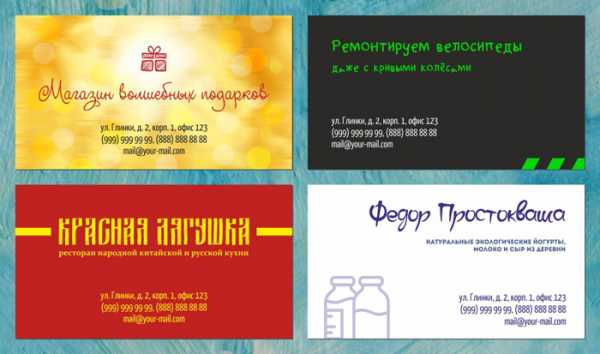
Если вы хотите взять «необычный» шрифт для своей визитки, но не уверены, выполняет ли он хотя бы одно из условий выше (и нужно ли ему их выполнять), забудьте о нем и посмотрите или вспомните, какие шрифты обычно используются для набора книг.
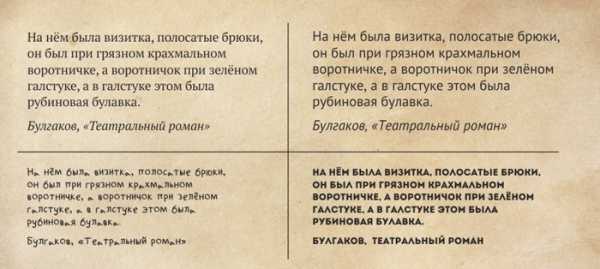
Такие, которые легко читать, как в двух верхних примерах.
Вот самый простой способ разделить шрифты на несколько групп в виде небольшой блок-схемы (не зря же я получал высшее образование по математической лингвистике). Начнем с вопроса «Подходит ли шрифт для набора большого количества текста?»
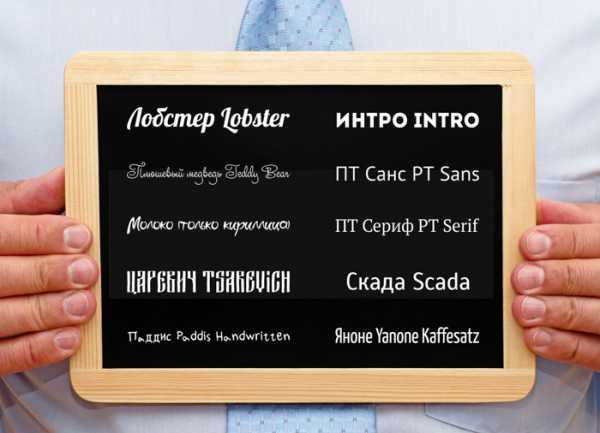
Небольшой гид по использованию шрифтов в визитках
Выбор шрифта – важный момент в создании любого дизайна, так как каждый шрифт вызывает определенные ассоциации. Данный пост является небольшим гидом по шрифтам, предложенным в нашем онлайн конструкторе визиток и использует исторические и другие факты, чтобы показать какие ассоциации эти шрифты вызывают.
C засечками или без
Исторически все шрифты делятся на два больших класса: шрифты с засечками (serif), небольшими черточками на концах букв, и без засечек (sans serif, от французского «без засечек»).
Шрифты с засечками появились в печатном деле гораздо раньше. Засечки были заимствованы из древнеримского написания, где, вероятно, они были побочным эффектом высечки букв на камне. Из-за этого вместо термина serif иногда используют термин Roman (римский) в названии шрифта (например, Times New Roman)
Шрифты без засечек (san serif) еще часто называют Готическими (Gothic), так как готические шрифты имитируют письмо пером, в котором нет засечек, или Гротесками (Grotesque), так как в 19-м веке шрифты без засечек стали часто использовать в заголовках.
Принято считать, что шрифты с засечками более удобны для чтения в больших текстах, в то время как шрифты без засечек более привлекательны с эстетической точки зрения. Поэтому при создании визиток чаще используются шрифты без засечек. Однако все зависит от общего стиля визитки. Например, шрифты с засечками будут хорошо смотреться в винтажных дизайнах.
Шрифты – аналоги
Очень часто встречаются практически аналогичные шрифты (например Arial и Pragmatica). Причина проста – это версии одного и того же успешного шрифта, созданные конкурирующими компаниями – производителями печатного оборудования. Часто название компании-производителя добавляется к названию шрифта (Monotype Cursiva – компания Monotype, Palatyno Lynotype – компания Linotype)
Основные шрифты с засечками
Times New Roman – шрифт с засечками, созданный в 1931 году специально для газеты Times. Times использовала его в течение 40 лет. С тех пор шрифт стал невероятно популярен в газетном деле и книгопечатанье. Если Вы книгоиздатель или хотите, чтобы Ваша визитка ассоциировалась с английской газетой начала XX века или просто хотите придать визитке винтажный стиль, то Times New Roman – ваш выбор. В онлайн конструкторе визиток ЛемонПринт мы предлагаем большое количество вариаций шрифта Times New Roman различной степени «жирности» и ширины.
Courier (аналог: Courier New) – шрифт с засечками, созданный в 1955 году и имитирующий текст, получающийся на механической печатной машинке. Данный шрифт использовался Министерством Иностранных Дел США, а также стал стандартом для телесценариев и для отображения кода компьютерных программ и сообщений на компьютерных терминалах командной строки (то, с чем мы ассоциируем хакеров, набирающих код на черном экране). Как результат, шрифт ассоциируется со способностью выйти за рамки и свободой. Кроме того, отлично подходит для коротких цитат.
Основные шрифты без засечек (Гротески)
Franklin Gothic – шрифт без засечек. Шрифты без засечек появились в 19-м веке под названием Гротески. Отказ от засечек был очень важной вехой в типографике, так как ранее на протяжении многих веков шрифты были с засечками, имитируя рукописный текст пером. Гротески использовались в основном в заголовках, и потому чаще встречаются в жирных вариантах. Franklin Gothic появился около 1902 года и активно использовался в заголовках для книг и газет. Его основное начертание – экстра жирное. Именно оно и представлено в нашем редакторе.
Arial (аналоги: Helvetica, Pragmatica) – это нео-гротеск (современная версия гротесков), шрифтов без засечек. Шрифт Helvetica был создан швейцарским дизайнером Максом Мидингером в 50-60-х годах XX-го века. Этот шрифт вобрал в себя результат таких движений в дизайне как Супрематизм и Конструктивизм, целью которых было упрощение и чистота геометрических форм. Он более округлый и гораздо более пропорциональный, чем классические «старые» Гротески. Шрифт Helvetica получил очень широкое распространение. Arial и Prgamatica – это версии шрифта Helvetica, созданные позднее другими дизайнерскими агентствами. Все три шрифта практически идентичны и идеальны для визиток. В онлайн конструкторе ЛемонПринт мы предлагаем большое количество вариаций шрифта Arial различной степени «жирности» и ширины. Если вы стремитесь к современному и минималистичному дизайну – это Ваш выбор.
Futura (аналог: Futura ParaType), Century Gothic – шрифты из семейства геометрических гротесков. Как видно из названия, эти шрифты основаны на максимально геометрически правильных и простых формах. Появление таких шрифтов, в основном, связано с течением Баухаус. Геометрические гротески наиболее хорошо смотрятся в сочетании с такими же простыми формами. Очень стильные шрифты, но будут хорошо смотреться только на тех визитках, где очень мало текста и много пустого пространства.
Помимо этих основных шрифтов, в нашем конструкторе визиток представлен еще большой набор Гротескных шрифтов различного начертания. Современные (такие, как Play), стилизованные под кисть (такие, как Pollock), имитирующие трафарет (такие, как Glasten) и много других.
Каллиграфические шрифты
Каллиграфические шрифты имитируют рукописный текст. В цифровую эпоху их появилось огромное количество. В нашем редакторе представлены порядка 10 различных вариаций каллиграфических шрифтов, имитирующих современное, старинное и даже детское рукописное письмо, включая всем известный Lobster. Такие шрифты смотрятся очень красиво, однако подойдут больше людям творческих профессий. Кроме того, текст, написанный каллиграфическими шрифтами, очень сложно читать. Поэтому при создании визитки используйте их для одного или двух самых крупных слов (например, имени и фамилии) и постарайтесь использовать максимальный возможный размер шрифта.
Интересно, что до компьютерной эры большинство логотипов, магазинных и других вывесок были сделаны не печатным текстом (из-за технической сложности), а выгравированы мастерами или художниками и подражали рукописным текстам различных эпох, что выглядело очень элегантно. Например, посмотрите на надписи на логотипе Cadillac или даже Ford. Cо второй половины 20-го века ситуация изменилась, и на логотипах стал чаще встречаться печатный текст. Но, возможно, Ваше лого или название компании, должно быть написано именно каллиграфическим шрифтом?
Читайте также
В каком формате лучше посылать макеты в типографию для изготовления печатной продукции?www.lemonprint.ru
Шрифты для визиток / Блог — визитки, печать визиток, заказать визитки
Как правильно выбрать шрифт для визитки
Как выбрать шрифт для визитки? Какой размер шрифта считается самым оптимальным? Можно ли использовать разные шрифты на визитной карточке? И вообще, как с помощью шрифта сделать визитку по-настоящему привлекательной? На эти и другие вопросы вы найдете ответы в этой статье.
На данный момент существует огромное количество самых разнообразных шрифтов, а их библиотека постоянно пополняется, предоставляя дизайнерам все больше пространства для творчества и интересных решений. Однако, не стоит забывать о том, что простота — ключ к элегантности! Поэтому, давайте сразу поговорим о том, какие шрифты не стоит использовать в своем дизайне. Плохой шрифт – плохой имидж.
- Comic Sans – слишком детский шрифт. Разве что, вы рекламируете товары или услуги для детей;
- Papyrus – комментарии излишни, не предназначен для деловых документов. Или в качестве материала для печати вы намерены использовать древнеегипетский папирус?)
- Arial – потому, что он везде! Вместо него используйте Calibri;
- Courier New – предназначен для написания сценариев. Если вы не хотите, чтобы текст на вашей визитке напоминал титры к голливудскому блокбастеру, не стоит использовать этот шрифт.
Так, какой же шрифт выбрать? Мы предлагаем простое решение – воспользуйтесь конструктором vizitka.ua! Сотни эксклюзивных шаблонов уже готовых использованию! С помощью нашего конструктора вы сможете с легкостью отформатировать свою визитную карточку, применив к ней самые разнообразные шрифты. Попробуйте, вам понравится! Итак, если:
— ваш бизнес связан со сферой науки, образования, юриспруденцией используйте Verdana;
— для всех специальностей, связанных с природой лучший выбором, станет Georgia;
— для сферы красоты и здоровья подойдет любой красивый прописной шрифт, например, Veles.
Используйте шрифты с умом, сделайте ваш дизайн простым, понятным и уникальным! Успехов Вам!
www.vizitka.ua
Поиграем шрифтами: как выбрать хорошую гарнитуру для визитки
Маленькая визитка — товар, который заказывают часто и сразу помногу. В большинстве случаев заказчик приходит в типографию с готовым макетом визитной карточки, с которого мы и печатаем. Но честное слово, глядя на некоторые макеты, особенно на их шрифтовую часть, становится откровенно жалко тех, кому эти визитки будут вручаться.
Мы уже писали здесь про пять правил корпоративной визитки. Давайте сегодня подробнее поговорим о выборе шрифта для этого важного бизнес-аксессуара.
Наш дизайнер, милая и нежная, но чересчур эмоциональная Маша Гутенберг уже высказала в своем ЖЖ мнение на тему «поиграть шрифтами» и свои соображения об использовании в дизайне полиграфии оригинальных шрифтов (осторожно: 18+ и местами очень непечатно). Мы постараемся рассказать о том же самом, но более литературно.
Главное правило — легко прочитать
Зачем вообще нужна визитка? Точно и легко передать кому-то контактную информацию. Поэтому при подборе шрифта для визитки надо помнить два правила:
- Текст должен легко читаться. Вы должны четко различать все символы, буквы и цифры.
- Текст должен быть достаточно крупным. Мелкий бисер никто не будет разглядывать в лупу.
На визитной карточке размером 90×50 мм, не так много места, на котором надо разместить контактные данные, имя и фамилию, а также оставить место для корпоративной идентификации или элементов оформления. Всё это должно смотреться органично и не мешать друг другу.
Для визиток рекомендуется использовать шрифт 10-14 кегля. Это оптимальный размер черного шрифта на белом фоне, который человек с достаточно хорошим зрением прочтет без труда. Мы не рассматриваем цветовые решения и контрастность текста и фона — только шрифт. Хотя встречаются оригиналы, которые помещают красный текст на розовый фон, например.
Выбирая шрифт для визитки, предварительно распечатайте его на листе и посмотрите, сможете ли вы хорошо разобрать напечатанное с расстояния вытянутой руки.
Какие шрифты выбрать
К читабельным шрифтам для визиток относятся популярные рубленые шрифты Arial, Helvetica, Calibri, Verdana, Tahoma, Century Gothic. Шрифты с засечками, типа Times или Garamond для визиток использовать можно, но осторожно — лучше приберегите их лучше для больших печатных текстов.
Если вы, например, дизайнер, фотограф или еще какая-то творческая личность, вы можете использовать в дизайне своей визитки и рукописные, и прочие фигурные шрифты. Напишите свое имя или название компании шрифтом, стилизованным под древнекельтские руны, рукописный текст или арабскую вязь. Но телефон и адрес пишите нормальным шрифтом, потому что этот блок обычно выполняется мелкой гарнитурой, и разобрать все эти завитушки и декоративные хвостики будет непросто.
Посмотрите на примеры шрифтового оформления визитки, которые Маша сделала для иллюстрации этого поста. На всякий случай, сразу предупреждаем: адрес и телефон Маши на этих иллюстрациях — вымышленные, можете не пытаться писать или звонить.
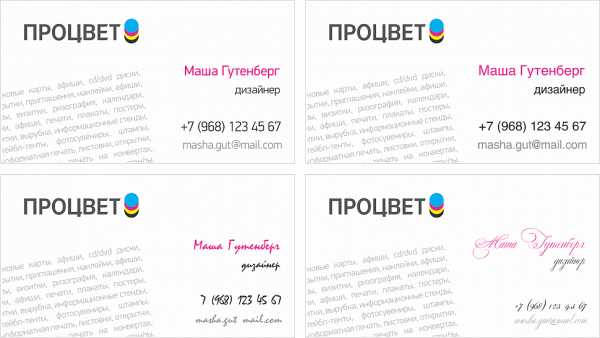
Два верхних варианта — это наш процветовский корпоративный шрифт слева, и стандартная Helvetica справа. Два нижних — какие-то наспех подобранные «из красивых». С какой визитки вам легче считывать информацию?
Если есть фирменный стиль
Если у вас есть готовый фирменный стиль — в нем обязательно должен быть пункт о корпоративных шрифтах и правилах их использования. В этом случае вместе с техническим заданием на печать будьте любезны предоставить и сам шрифт отдельным файлом, и правила.
Правда, если ваш корпоративный шрифт — нечто трудночитаемое, то используйте его для чего-нибудь другого: для слоганов на баннерах, для вывесок. Черт с ним, даже для слогана на самой визитке — все равно он там никому не нужен, если честно. Но напишите контактную информацию человеческим удобным шрифтом. Хотя бы стандартным и очень читабельным Calibri.
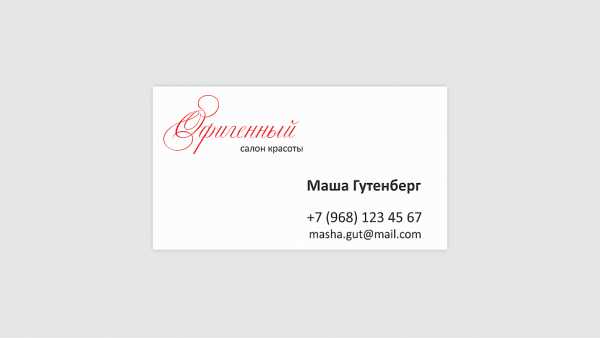
Не устраивайте мешанину
Некоторые особо креативные дизайнеры умудряются впихнуть в визитку несколько разных шрифтов, считая это оригинальным и нестандартным ходом. На самом деле это обычная безвкусица.
В хорошей визитке может быть использовано максимум два шрифта: один для слогана, корпоративного лозунга, логотипа и так далее. Здесь вы вольны брать любой шрифт, который вам понравится — выше мы уже сказали об этом. Второй, читабельный и понятный — для персональной и контактной информации. Вы можете использовать разные начертания: жирное, курсивное, но это должна быть одна гарнитура. Посмотрите на картинку: Маша показывает нам, как можно делать, и за что дизайнеру надо отрывать руки и гнать из профессии.
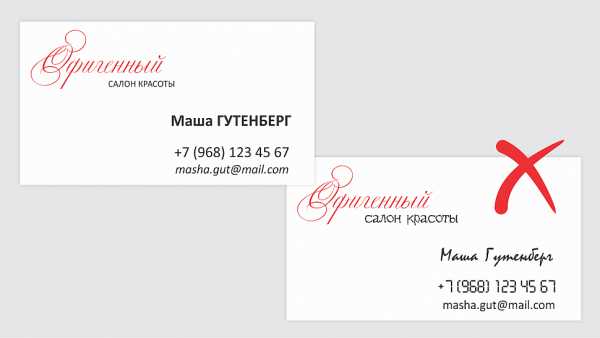
И, конечно, реклама
Да, а что? Мы же в своем собственном блоге, так что имеем полное право на рекламу самих себя любимых. И рекламируем.
Мы не только хорошо печатаем визитные карточки всех форматов и типов. Если нужно — легко разработаем дизайн стильных, современных, удобных и полезных визиток. А если очень нужно — доставим в любую точку России. Вдруг вы из Хабаровска, например?
Звоните, пишите, приходите в гости поиграть шрифтами. Будем рады.
pro-color.ru
Как правильно выбрать шрифты для баннера или визитки – Ярмарка Мастеров
Сегодня хотелось бы затронуть тему шрифтов.
Очень часто, заказывая баннер, визитки или что-то еще, Вы просите сделать надпись «каким-нибудь красивым шрифтом с финтифлюшками».
Но всегда ли это уместно и правильно? Какие шрифты можно и нужно сочетать, а какие уже вышли из моды?
Итак, давайте разбираться.
Существует 6 основных шрифтов, которые есть на каждом ПК и пользуются особой популярностью. Это Arial, Tahoma, Verdana, Times New Roman, изредка Georgia и Courier.
Шрифты Arial и Times New Roman узнает каждый, ведь ими написана львиная часть договоров, счетов, сайтов и т.д.
Получается, эти шрифты избитые и им не стоит уделять внимания? Отнюдь. Эти шрифты как нельзя кстати подойдут к каким-либо документам и классическим визиткам. Они читаемы и привычны.
Что же касается шрифтовых сочетаний – это настоящее искусство. Красота типографики не знает границ. И хотя не существует абсолютных и общепринятых правил, которым необходимо следовать,- очень важно, чтобы Вы понимали и применяли некоторые хорошо зарекомендовавшие себя принципы.
Итак, попробуем выделить основные приемы:
1. Используйте не более двух (или может быть, трех) шрифтов, создавая художественный текстовый блок, визитку, буклет или скрап-страничку. Разумеется, могут быть исключения, но в большинстве случаев использование большего количества шрифтов придаст вашей работе неопрятный неструктурированный вид.
2. В визитках старайтесь использовать максимально читаемые шрифты. Ни кто не будет разбирать с лупой Ваш адрес на визитной карточке, написанный витиеватым рукописным шрифтом 5 размера.
3. То же самое правило для наружной рекламы. Шрифт должен быть в первую очередь читаемым. Чтобы пары секунд было достаточно для полного понимания написанного.
4. Правильно подбирайте цвет шрифта.Наибольшего эффекта можно добиться, противопоставляя ахроматичные и хроматичные цвета, дополнительные цвета, а так же холодные и теплые. Не забудьте, что теплые цвета выделяются на странице, тогда как холодные отступают на второй план.
5. Используя цвет шрифта близкий к фону – добавьте ему тень, чтобы выделить. Используя более темный цвет шрифта – выделяйте его от фона обводкой или свечением.
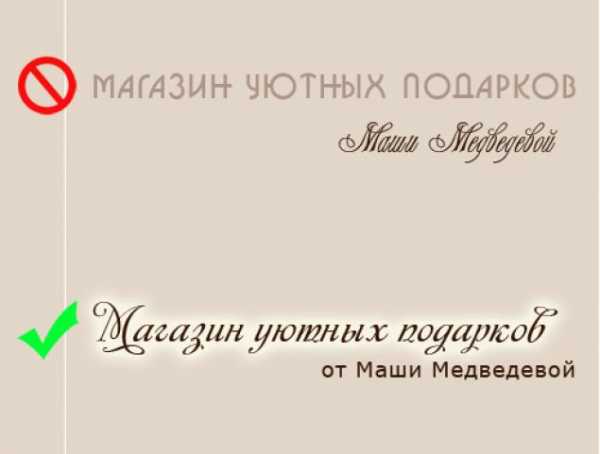
6. Старайтесь не использовать одну группу шрифтов – это создаст резонанс. Однако шрифты с минимальными отличиями при правильном подборе могут придать вашей работе гармоничный и слегка официальный вид.
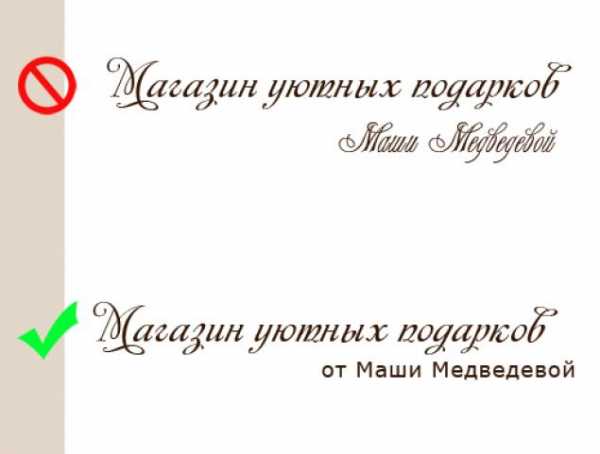
7. Контраст – важная составляющая шрифтового оформления. Это самый эффективный инструмент для создания смыслового ударения. Это может быть как контраст стилей, так и цветовой контраст. Выделяйте более яркими цветами или крупными буквами ту часть текста, к которой хотите привлечь наибольшее внимание.
8. Как создать контраст с помощью размера, совершенно очевидно: крупный шрифт нужно противопоставить мелкому. В этом случае действует только одно правило – не робейте! Если вы уж решили создавать контраст с помощью размера, сделайте это нарочито броско – не дайте людям возможности подумать, что это ошибка.
9. Контраст толщины – один из наиболее простых и эффектных способов привнесения в вашу работу большей зрительной привлекательности. Если вы уж используете этот вид контраста, здесь действует все то же правило – не робейте. Если контраст не сильно заметен, он будет выглядеть как ошибка. Шрифты из разных групп, как правило, уже отличаются по толщине, подчеркните это отличие.
10. Самый простой способ создать контраст – это противопоставить прописные буквы строчным. Но ни в коем случае нельзя дополнять чересчур витиеватый рукописный текст сложным прописным с засечками. Чем сложнее текст, который мы хотим выделить, тем проще должен быть текст второстепенный.
Очевидно, что выбранный шрифт и по форме, и по цвету должен усиливать или хотя бы поддерживать основное стилистическое решение вашей работы и ее идею. Тем не менее, главным критерием при выборе шрифта пусть будет ваш личный вкус и чувство прекрасного.
Всем хорошего дня и приятного творческого процесса.
www.livemaster.ru
26 тисненных дизайнов визиток
Маркетинг, это основа строения любой компании. При правильной маркетинговой политике, ваша компания будет процветать и привлекать к себе все новых и новых клиентов. Конечно же, не стоит забывать и о важных мелочах, как например обмен визитными карточками. Эти кусочки бумаги содержат очень важную информацию о вас, вашем сайте, номере телефона, адресе электронной почты, а также месте вашего расположения и роде деятельности.
При создании качественной типографической визитки с тисненными узорами или шрифтами на бумаге, необходима специальная типографическая машина. К сожалению, она имеется далеко не во всех типографических компаниях. С ее помощью можно создавать выдавленные буквы и образы, которые отлично украсят любую визитную карточку, придав необычный образ бумаге. В этой подборке вы увидите 26 примеров визиток с тисненными узорами и шрифтами.
Визитка с резным деревом Cleverly Cut
Разноцветные логотипы на визитке Forget Technology
Узорная бумага на визитках KG Creative
Визитка графического дизайнера Джастина Анонуево
Чистый и аккуратный дизайн визитки PAR
Нежные тесненные шрифты на визитке Bulldog Drummond
Тесненная иллюстрация на визитной карточке Distillery
Инфографика и иллюстрация на визитке thomas + kristine
Визитки свадебной компании White Wedding
Мордашки-яблоки на визитке Good Apples
Визитка дизайнера Кима Бентли
Визитка с иллюстрацией Scarpetta
Тесненные узоры и узорные шрифты на визитке дизайнера Коллин Элис
Стильная визитка Скотта Сальватора
Яркие зеленые цветы на визитке свадебной компании Dariana Cruz
Стильная типографика на визитке графического дизайнера Tiago
Симпатичные визитки в стиле ретро Identity Kitchen
Логотип в виде указателя на визитной карточке -Portland Sportsman
Аккуратные шрифты и чистый дизайн визиток Раяна Принса
Жирный шрифт в качестве логотипа на визитке Yaili
Креативные прописные шрифты на визитной карточке Самера Зайдеха
Визитка фотографа Доуг Маранда
Античные шрифты и теснение на визитках фотографа Джессики Моррси
Простой дизайн визитной карточки у Якоба Варда
Сочетание оранжевого и серого в ретро стиле на визитке Faber Design
Тесненный логотип на визитке Duplex
Автор – designm
Перевод — Дежурка
Комментарии
Оставить ответ
Похожие статьи
Случайные статьи
www.dejurka.ru
Ликбез онлайн-версии фотошопа. Шрифты и изготовление быстрой визитки
Этот мастер-класс в помощь тем, кто не умеет работать в фотошопах и аналогичных программах. Или имеет только поверхостное ознакомление с ними. Мы разберем все инструменты онлайн-версии фотошопа, которую не нужно ни скачивать, ни устанавливать. Расскажу, где искать и как устанавливать красивые русскоязычные шрифты. Я открою пару интересных секретов быстрой обработки изображения. И расскажу, как быстро сделать визитку и подготовить ее к печати дома.
Я заметила, что на Ярмарке Мастеров очень много мастеров, не имеющих опыта работы в фотошопе. Программа дорогая, не все могут ее себе позволить. Кроме цены – она также весьма сложная и разобраться без специальных мастер-классов в ней тяжело. Хочу немного помочь всем тем, кому нужно делать бирочки, визиточки, баннеры или просто подпись к фотографии – это легко и просто делается без скачивания спец-программ. Мы будем использовать так называемый фотошоп-онлайн. Внимание! Нам нужен будет фотошоп с такой заставкой вначале:
Нашли? Отлично! Пока мы не начали работать – давайте подберем какие-нибудь интересные шрифты! Именно подбор шрифтов – главная проблема для многих. Во-первых, где их брать? Во-вторых – как устанавливать? Все очень просто. Шрифты находятся в интернете. В поисковик забиваем «шрифты скачать». Сайтов очень много. Как выбрать среди них?
Критерии первый: должна быть возможность как-то выбрать просмотр только кириллических или русских шрифтов. Везде их называют по-разному. Суть в том, чтобы нам показали максимальный выбор шрифтов с русской раскладкой. Конечно, это актуально в том случае, если визитки, бирочки или баннер вы хотите заполнять на русском языке. Если вам нужны латинские шрифты – все просто. Качать можно любой понравившийся – 90% шрифтов именно англоязычные.
Вы смогли отрегулировать фильтр поиска или же там просто русские шрифты выделены отдельной категорией. Заходим. Вы увидите название шрифтов, под ним картинка – название шрифта, написанное самим шрифтом. Шрифтов сотни и тысячи. Не стоит пытаться скачать все. Выбирайте те, что нравятся. Безусловно, всегда полезны рукописные; “bold”, т.е. жирные; различные “old”, т.е. под старину; готические и прочие. Часто, принадлежность к какой-либо категории у шрифта написана в названии. Вы часто можете увидеть один и тот же шрифт, который сначала идет отдельно bold, потом italic (курсив), затем bold italic. Почему так? Ведь мы привыкли, что выбираешь шрифт, а потом отдельной кнопкой делаешь его жирным, курсивом или прочее. У нестандартных шрифтов такой возможности нет. Если шрифт состоит из тонких букв – таким он и останется. И толстые буквы будут только, если вы скачаете отдельный такой же шрифт с подписью bold. Есть еще варианты, когда буквы прозрачные, т.е. есть только их контур, или же заполнены некоторым узором, а не просто черные. В общем, полистайте, посмотрите – это ужасно интересно. Руки так и тянутся все скачать 🙂
Теперь второй критерий: возможность посмотреть шрифт до скачивания! Обычно есть кнопка «посмотреть шрифт» или «весь шрифт». Или при нажатии на шрифт – он открывается в окне и там будет его раскладка. Выглядит это так:
Зачем это нужно? Дело в том, что, даже когда вы выбираете только кириллические или русские шрифты… все равно среди них как минимум половина будет без русской раскладки! Теперь как разобраться в таблице букв. Сначала идут латинские буквы – большие и маленькие. Потом цифры, затем значки… и только после этого идет русская раскладка – также больших и маленьких букв. Если на русской раскладке вместо букв пустые окошки или черные квадратики – у этого шрифта нет русской раскладки! Бывает, что у шрифта есть только большие или только маленькие буквы. Конечно, лучше всего, если присутствуют все буквы – и большие, и маленькие. Но это не обязательно. Наличие знаков – тоже желательно. Хотя бы та же @ — нужна нам для того, чтобы написать в визитке почту. Но, если шрифт вам очень нравится, а «собачки» там нет – не расстраивайтесь – найдете этот значок в другом шрифте, хотя бы в том же стандартном.
И так. Шрифты накачали. Установить их очень просто. Если у вас старая версия оперативной системы, то Мой компьютер-Windows-Fonts. Распаковываем шрифты из архива, если они были в архиве. Переносив шрифты туда без папок! Прямо в корень. Он их начнет устанавливать после этого сам. Если у вас новая оперативная система (хотя бы семерка) – тогда просто щелкните два раза на каждой файле шрифта – и он начнет устанавливаться сам. Шрифты тогда появятся у вас в ворде, фотошопе и также онлайн его версии (все программы желательно открыть заново после установки шрифтов). Теперь можно приступать к изучению фотошопа-онлайн.
Сначала ликбез. Разберем окно, которое открывается при старте.
1. Создать новый рисунок. При открытии появляется окно. Первая строка — «имя» — можно не вводить. Затем — «предварительные настройки» — тут есть некоторое количество стандартных форматов, которые можно выбрать. Если вы не хотите стандартный размер изображения – выбираете его сами, выставив ширину и высоту ниже. К сожалению, выбор только в пикселях, разрешение выставлять нельзя! Если хотите разрешение побольше – лучше найти как-то файл с изображением в интернете и открыть его в фотошопе. Какая картинка не важна – сверху нарисовать можно что угодно) Главное, получить файл с изначально высоким разрешением.
2. Загрузить изображение с компьютера. Тут все понятно. Кушает он достаточно много форматов, в том числе, и psd – формат, сохраняющий слои.
3. Можно открыть файл сразу из интернета. Когда нашли в интернете понравившуюся картинку, ее можно не скачивать, а нажать правую кнопку мыши и выбрать «копировать адрес изображения».
4. Открыть изображение из библиотеки – т.е. из всяких соцсетей.
5. Последнее – открыть с телефона.
Мы создали или открыли файл. У нас есть горизонтальные вкладки и вертикально расположенные окна инструментов.
Горизонтальное меню (сверху):
Файл: понятно — тут открываем, сохраняем и прочее.
Редактировать: тут инструменты для выделения, поворота, копирования и вставки. В какой-то степени, они дублируют основные инструменты, которые находятся на вертикальной панели слева. Редактирование – Free transport – это возможность повернуть или отразить рисунок, а также уменьшить. Действует только на слой! Чтобы пропорции изображения не менялись – зажмите shift. Чтобы отразить рисунок – зажмите правую кнопку на уголке и переместите ее слева направо, чтобы отразить горизонтально и сверху вниз, чтобы вертикально. Только shift не зажимайте. Если зажать shift – изображение повернется, будто вы его просто повернули верх ногами 🙂
Изображение: тут можно переворачивать наш файл. Именно файл! Файл состоит из нескольких слоев – переворачиваться будут все слои. Тут же есть отразить по вертикали или горизонтали, также можно менять размер файла.
Слои: меню по работе со слоями. Почти все, что там есть – дублируется другими инструментами.
Коррекция и фильтр: обработка фотографий. Свет, яркость, цветность, различные деформации, формы и прочее. Честно говоря, там надо каждому самому покопаться. Вместить сюда курс коррекции фотографии и использования фильтров… лучше отдельным постом, хотя тут и так постов на эту тему много. Тут есть даже такие фильтры… которых в фотошопе нет! Например, калейдоскоп 🙂 А еще есть инструмент «придание точечного стиля» – из любого рисунка можно сделать схему для вышивки!
Просмотр: тут есть возможность открывать разные окна, которые очень нужны. Окна горизонтальных дополнительных инструментов, навигатор (чтобы приближать), слои (те самые!), журнал (она же история, чтобы можно было вернуться назад – ужасно полезно! Журнал свой для каждого открытого файла.
Язык и помощь – тут тоже все ясно 🙂
Рассмотрим левое вертикальное окно. Условно инструменты можно поделить на инструменты для выделения, рисования и коррекции. Рассмотрим первый блок.
Когда вы жмете на одну из кнопок инструмента – в горизонтальном окне сверху появляются доп. функции (на сером фоне).
Обрезка – инструмент, позволяющий не только обрезать, но и контролировать размер обрезки края. Тут все ясно – тыкаем на инструмент, обрезаем картинку по краю, например. Если сверху на серой полосе у нас стоит в окне «без ограничений» — то можно просто обрезать изображение так, как хочется. Если нам нужно сохранить соотношение сторон (по соотношению сторон открытого файла) – например, для того, чтобы потом напечатать фотографию для альбома – то вбираем «соотношение сторон». По умолчанию стоит 1:1 – т.е. с сохранение пропорций сторон. Если нам нужно задать какой-то определенный размер, то выбираем «выходной размер», ставим нужное количество пикселей по вертикали или горизонтали. Это удобно, например, для создания аватарок. Выставлять все параметры нужно до того, как вы начали обрезку файла!
Выделение – все логично. Что-то выделяем, затем, чтобы переместить выделение, не вырезая картинку, просто жмем на выделенный участок, а чтобы вырезать и использовать выделенное где-то еще, его можно перетащить с помощью инструмента «перемещение». Пробежимся по дополнительным функциям. Значит, два вида выделения: прямоугольное или в форме эллипса. Ограничение – тоже, что в инструменте «обрезка». Растушевывание – это возможность сделать край при выделении не резким, а растушеванным. Эффект от инструмента «в форме эллипса» показан на первой картинке, а от инструмента «прямоугольное выделение» на второй картинке. Здесь края прямоугольника за счет растушевывания можно красиво сгладить. На примере размер растушевывания =17. Но это все зависит от начального разрешения файла.
Перемещение – нужен в работе со слоями, о которых я расскажу позже. С помощью него можно перемещать объект на слое по нашей картинке и перемещать слои в других файлы.
Лассо – это также инструмент выделения, но более тонкого, чем простое выделение. На мой взгляд свободное лассо вообще бесполезно. Гораздо удобнее многоугольное лассо. С помощью него можно очень точно выделить любой объект. Чтобы край был не резкий, можно даже немного растушевать. Чтобы вырезать объект, сначала его приближаем (инструмент «навигатор» справа). Затем левой кнопкой мыши идем вдоль края, отмечая как бы точки перегиба лассо там, где наша линия меняет направление. Этот же инструмент есть и в нормальном фотошопе. Там им пользоваться очень удобно, а вот в онлайн-версии много глюков. Во-первых, чтобы удобнее вырезать по линии объект – его нужно приблизить, а, значит, объект не влезет весь на экран и его нужно передвигать. А в онлайн версии сдвинуть окно нельзя во время выделения. Точнее можно, но, почему-то, выделенная вами область тут же смещается вслед за окном. Короче, неудобно! Ниже, в МК по созданию визитки я поподробнее расскажу, как вырезать, также используя дополнительно инструмент «волшебная палочка».
Волшебная палочка – это автоматическое лассо. Не пользуйтесь этим инструментом, если хотите аккуратный результат. Пользовать им можно только на очень контрастных изображениях. Хорошо на черно-белых. Но граница все равно будет неровной. Это убыстряет процесс, но только если нет градиента цветов – а он есть почти всегда. Использовать ее можно только в комплексе с другими инструментами выделения. Внизу, на мастер-классе визитки я это покажу.
Второй блок инструментов:
Карандаш и кисть – инструменты рисования. Честно говоря, эти инструменты чаще используют те, у кого есть планшет и те, кто умеет рисовать. Это особенно относится к карандашу. Не понимаю, что с ним делать. А вот «кисть» очень полезный инструмент. Заходим в меню кистей.
Сверху появляется дополнительные иконки – чтобы открыть меню выбора кистей нужно нажать на изображение кисти рядом со словом «кисть:». Там вы видите стандартный набор кистей. Можно достаточно интересным методом создать свою кисть – выбрать круглой она будет или квадратной, какой нажим, где разрезы в контуре и прочее. Но давайте научимся использовать уже готовые кисти.
Кроме стандартного набора тут есть некоторый набор, который можно загрузить из архива программы. Нажимаем кнопку «другие параметры». Там потыкайтесь – есть штук 20 разных наборов кистей, вполне даже приличных. Чтобы они добавились – жмем добавить. Для меня оказалось абсолютной неожиданностью, что функция загрузить кисти с компьютера тут есть… вот только стандартный тип файла кистей .abr он не видит. И требует какой-то непонятный .pbr! Что за невидаль? Сунулась в интернет. Все кисти только в формате .abr! И люди, задающих один и тот же вопрос – где взять кисти в странном формате .pbr? Попробовала взять кисти из своего нормального фотошопа и сохранить в странном формате, но фотошоп отказался. Интернет ищет только кисти формата .abr. Это ужасно печально, так как выбор стандартных кистей из тех, что он подгружает из своего архива, невелик. Нет красивых завитушек, мало растительного орнамента… Ну, что поделать. Но, если вы используйете фотошоп или его бесплатный аналог, то использовать кисти нужно. Для этого – вводим в поисковик «кисти для фотошопа». Обычно рядом с кистями есть и инструкция по их установке. Для каждой программы по-разному.
Ладно, вернемся к другим функциям кистей. Вот вы загрузили разные кисти из архива. Можно менять их размер. Делать кисть прозрачнее. Есть также функции Hard tip – т.е. резкий край, диффузия – рассеивает узор кисти. А инструмент «рассеять» – актуален только если вы хотите изобразить летящие листья или рассеянные звезды. Т.е. жмешь несколько раз – а листья появляются не в том месте, где нажимаешь, а в случайном месте. В большом открывающемся меню еще есть три параметра – диаметр, регуляция той самой рассеивания – расстояния между рассеянными объектами и твердость.
Ластик – тут все ясно. Можно стирать уже нарисованное. Удобно, что ластик действует на слой. Т.е. можно нарисовать что-то на отдельном слое – и, если потребуется стирать, стирать будем на отдельном слое. Я постаралась показать. На мишку я наложила другой слой и легко смогла с него стирать, не затрагивая мишку. Также можно и рисовать. Кстати, край ластика тоже можно рассеивать. Формы ластика – это те же формы, которые мы загружали в кисти.
Заливка – ну… это возможность заливать что-то цветом. Честно говоря, удобна только для заливки основного фона. Действует на слой.
Градиент – это та же заливка, только красивым градиентом. Инструмент работает так: левой кнопкой мыши отмечаем начальную точку, не отпуская кнопку, тянем в одну из сторон – чем дольше тянем – тем более растянутый будет градиент. Можно тянуть по горизонтали, можно по диагонали. Есть стандартные градиенты, можно создать самому. Для этого на горизонтальной шкале градиента нажмите в любом месте – появится зарубка. Каждую такую зарубку можно двигать, менять ее цветность и непрозрачность. Там же можно делать линейный градиент, радиальный, с повторами и прочее… Активная зарубка обозначена черным треугольником сверху. Я ее отметила красным. Я убрала прозрачность – и в этом месте градиента стал виден нижний слой с мишкой.
Штамп – очень интересный инструмент коррекции. Наведите курсор на то место, которое хотите «запомнить», нажмите ctrl – курсор поменяет форму на крест – и нажмите левую кнопку мыши. Чтобы текстуры лучше ложились в новое место – лучше использовать кисть с растушеванным краем. Затем переносите объект в другое место. Таким нехитрым инструментом я сделала мишке лишний десяток глаз… Но чаще всего инструмент применяют для коррекции дефектов кожи или же обрезанного края, который нужно дорисовать.
Рисование – это инструмент рисования прямоугольников, кругов и линий. Опять же можно сделать их прозрачными, можно добавить границу. Внутренняя часть фигуры будет заполнена тем цветом, что указан в горизонтальном меню справа, а цвет границы, если ее поставить хотя в 1 пикель, цветом, который указан слева внизу.
Дальше идут инструменты важные скорее для обработки фотографий.
Размытие и резкость – тут все ясно. Делаем что-то размытым или резким. Причем можно регулировать интенсивность и форму кисти.
Палец и губка – это странные инструменты. Некоторые люди используют палец для размытия дефектов. Губка – это что-то странное. Представьте, что у вас есть рисунок акварелью – и вы на него капнули водой и начали по нему возить губкой. Вот что-то такое…
Осветление и затемнение – все для работы с фотографиями.
Красные глаза – понятно, убирает красные глаза.
Точечная коррекция – это интересные инструмент для редактирования фотографий. Убрать родинку или прыщик? Нажали и готово! Даже лучше пальца) Штамп – это примерно тоже самое, но коррекция более автоматически сливает текстуры. А штамп просто накладывает изображение сверху.
Раздувание и дисторсия – это такое веселый инструмент, которым можно делать смешные рожицы с большими глазами или подправлять фигуру 🙂
Пипетка очень полезна – наводите на нужный цвет – и вот он в палитре…
А – это текст. Как раз тут множество шрифтов, которые мы себе установили. Можно менять размер, можно менять жирность (это называется стиль), курсив и прочее (в других редакторах так нельзя, только тут уже жирный шрифт можно сделать еще жирнее, а курсив… еще более наклонным :)), поменять цвет. Шрифт выбираем из тех, что установили себе на компьютер – программа использует шрифты с вашего компьютера. Шрифт всегда печатается на новом прозрачном (!!!) слое. Так что вы легко сделаете подпись к вашей фотографии.
Палитра! Тут не все так просто. Она тут аж в 4-х варианта. HSL, RGB, WEB и IMG.
IMG – это фактически не палитра. При открытии файла – программа считывает все цвета, которые в ней есть и отражает их.
WEB – это стандартная палитра, закомая вам по ворду. Она достаточно ограничена в цветах.
RGB – тут вы видите три круга с пересечением. Внизу линии – они меняют цветность каждого круга. От этого меняется цвет в центре пересечения трех кругов.
HSL – тут немного сложнее. Верхняя горизонтальная линия двигает кружок по цветовой окружности. Средняя – отвечает за интенсивность от белого до яркого цвета, нижняя – тоже от черного до яркого цвета. За счет этих двух линий кружок бегает по ромбу внутри окружности. Кроме того, за счет линейки дополнительных цветов в палитре справа можно к любому выбранному цвету сразу увидеть несколько близких тонов. Еще интересно. У каждого цвета есть свой номер. Это в том случае, когда вам нужно точно сохранить оттенок – можно просто ввести его номер.
Теперь о слоях. Это самое важное в фотошопе.
Если вы когда-то открывали Paint, то заметили, что там ты рисуешь всегда на одном и том же слое. Если что-то нарисовал – там оно и остается – ни сдвинуть, ни стереть, не повредив другую часть рисунка. А вот в фотошопах и его аналогах можно. Слой можно представить себе прозрачной пленкой. Вы можете нарисовать на каждом слое пленки разное, а потом легко двигать их между собой, при этом общая картина будет меняться. При этом слой можно сделать невидимым, если он вдруг вам мешает прямо сейчас. Слои можно менять местами. Всегда создавайте новый слой, когда собираетесь что-то рисовать. Когда создаете текст – слой создается автоматически, называется текстовым и отмечен буквой «А» в меню слоев. На текстовом слое нельзя рисовать, редактировать его можно ограниченно. Зато можно менять в любой момент шрифт и его цвет. Текстовый слой можно растрировать – т.е. превратить в растровый. Тогда менять шрифт уже будет нельзя, буквы на слое будут простым изображением, как и любой другой рисунок. Зато можно уже его редактировать всеми инструментами программы. Далее… не забывайте! Если вы рисуете что-то сами кистью – обязательно создавайте новый слой. Так как именно на слой направлено действие всех инструментов фотошопа. Если вы нарисуете что-то просто на слое с изображением и захотите потом что-нибудь стереть – не получится. Новая часть рисунка будет стираться вместе с изображением.
Как создать слой?
Красной стрелкой я отметила кнопочку. Новый слой будет виден в меню справа весь в серо-черных квадратиках, что означает, что он прозрачный. Галочка напротив слоя означает, что сейчас он видимый. Убираем галочку – и слой становится невидимым, хотя он и есть). Если зажать кнопкой слой и поднести к ведерку (справа от кнопки создания нового слоя) – слой будет удален. А если к кнопке создания нового слоя – слой будет скопирован.
Самая левая кнопка (обвела красным) – регуляция прозрачности и режим соединения слоев. Тут даже не сразу объяснишь, что это. Прозрачность – это понятно. А вот режим? Если на пальцах – нижний слой, как бы подложка. Режим можно применять только к слою, находящемуся над каким-либо слоем слоем. И он будет по-разному взаимодействовать с нижним слоем. Поменяете нижний слой – картина изменится. Вот примеры (верхний слой буквы, нижний слой мишка):
Это надпись сделана коричневым цветом, затем к ней применены некоторые режимы. Если это не надпись, а какое-то изображение – тут можно очень интересно поиграть. Тату сделать на плечо, синяк под глазом! Шутка-шутка 🙂 Также у нас есть еще интересная кнопка – стили слоя. Это третья кнопка слева (обвела красным). Вот как можно с помощью этих инструментов оформить текст: Тень снаружи, Тень внутри букв, Добавление объема и текстуры буквам, Свечение снаружи, Свечение внутри букв. В каждом инструменте там есть еще дополнительные функции – куда направить тень, насколько она интенсивная, насколько размыта и прочее.
Еще один важный момент. Любой открытый файл (если он не psd или tiff) в фотошопе будет отображаться как один слой с замочком. Замок – значит закрытый. Его нельзя ни двигать, ни редактировать. Просто щелкните два раза на замочке – и он сменится на галочку. Все – теперь с этим слоем можно делать что угодно. Слои можно передвигать – ведь от того, какой слой сверху – можно получить совершенно разные эффекты.
Кажется все по инструментам. Теперь еще пару секретов.
Если у вас фото на светлом фоне, но он отнюдь не белый. Что делать? Лучше бы вырезать и вставить на белый фон, но это бывает очень трудоемко… поэтому есть секрет. Коррекция – кривые. Там жмем на пипетку с белым. Затем направляем ее на фон.
И все. Другие цвета при этом остаются сочные и яркие. Если с первого раза фон не весь стал белым – тыкаем этим же инструментом в проблемное место. Кривые вообще хороший инструмент для коррекции яркости фотографии. Он более гибкий чем просто яркость-контраст.
Теперь, допустим. Вы нашли объект… но цветовая гамма вам чуток не подходит. Бантик фиолетовый, а вам бы такой же, но желтый. Коррекция-цветовой фон/насыщенность.
Потрясающий инструмент! Он полностью меняет цветовую гамму. Плюс можно менять яркость и интенсивность выбранной гаммы. При этом черный и белый не меняются. С помощью этого же инструмента можно спасти желтые, красные и зеленые фотографии, в которых не выровнен баланс белого.
Давайте теперь сделаем визитку-пятиминутку. Печатать ее можно дома или в типографии.
Сначала нам нужно создать файл нужного размера. Но у нас задавать размер можно только в пикселях. Визитка же должна быть 9Х5 см. Поэтому скопируйте шаблон из этой темы.Его-то мы и открываем в фотошоп-онлайне. Шаблон для визитки (9Х5 см, 300 dpi) находится в моих эскизах: https://cs1.livemaster.ru/storage/9e/6a/f69147ef3efec862b9fd05585e.jpg
Теперь открываем какой-нибудь файл, который будет нашей основной картинкой. Пусть будет тот же мишка. Он на белом фоне – это удобно. Но с белым фоном каждый может. Сейчас я научу вас убирать любой фон. Ведь красивый белый фон – редкость.
Инструментом «выделение» – выделяем нужную область, инструментом «перемещение» ( курсор должен измениться на ножницы) перетаскиваем мишку в наш шаблон. Он откроется новым слоем (справа виден новый слой 1). Его можно свободно двигать.
Чтобы было лучше видно белый фон у медведя – покрасим временно основной фон визитки в черный цвет. Не забывайте постоянно проверять на каком слое вы работаете – активный слой выделен голубым.
Наш мишка весьма контрастный – поэтому можно «волшебной палочкой» убрать белый фон, на котором он сидит. Жмем волшебной палочкой на фон вокруг мишки – он выделяется, жмем delete. Правой кнопкой мыши отменяем выделение и смотрим результат. Край не радует взор – зато быстро.
Приближаем с помощью навигатора справа, активируем лассо, выбираем многоугольное лассо. И дальше по чуть-чуть начинаем красиво ровнять край. Т.е. выделяем небольшие куски и удаляем лишнее кнопкой delete.
Также я показала различие между не обработанным краем, обработанным без растушевывания и с ним.
Лучше растушевать потом самому. Делаем это инструментом «размытие». Ставим интенсивность 50 и проходимся по всему краю чуть-чуть. Меняем цвет в палитре на белый, переключаемся на нижний слой визитки и красим его заливкой в белый.
Теперь давайте сделаем какой-нибудь текст. Инструментом «текст» пишем название. Пусть будет «Пушистый мишка». Выбираем шрифт, размер и цвет.
Сделаем буквам тень с помощью стиля слоев.
Затем я решила добавить небольшой «слоган» под названием. Я хочу, чтобы его цвет совпадал с цветом тени у букв про пушистого мишку. Беру «пипетку», тыкаю на тень – и вот у меня в палитре нужный цвет.
Пишу слоган. Мне кажется, что тут подходят какие-то небольшие буквы, прописные. Потом добавила контактные данные. В принципе, готово. Тут уже цвет и шрифт каждый подбирает по своему вкусу. Хотя, на мой взгляд бедновато получилось, зато ничего лишнего.
Но мне захотелось последний акцент сделать – добавить бантик. Переношу его из открытого файла так же, как и мишку, убираю белый фон, ровняю край. Затем использую инструмент free transport и поворачиваю его под углом. Пусть бант будет в углу. Чтобы он не закрывал текст переношу слой с бантиком под другие слои. Для этого просто выделите слой, нажмите левой кнопкой мыши на него и тяните вниз, не отпуская левую кнопку. Затем я сделала слой с бантиком чуть менее прозрачным – а то ярко. Теперь буквы контактов в этом цвете не смотрятся – изменим. А слою «уютные игрушки» сделаем белое свечение с помощью стиля слоев.
Ммм… еще немного подправила цветовую гамму – название теперь пусть будет светло-песочный, а тень фиолетовая.
Вуаля. Визитка-пятиминутка готова! Файл – save as – сохраняйте обязательно в двух форматах. Jpeg и pxd. Pxd – аналог формата psd – он сохраняем все слои, так что вы в любой момент сможете вернуться к вашему файлу, изменить поменявшийся номер телефона или еще что-то. К тому же, можно сохранить промежуточный вариант и не бояться, что он пропадет, пока вы пойдете в магазин за хлебом. Я вот, например, делаю бирку к каждому темари абсолютно индивидуально – к каждому пишу название, вставляю фотографию, описание и хайку. Так что файл, который можно постоянно редактировать очень-очень полезная вещь. Формат bmp – тоже полезен – он объемный, но, в отличие от jpg, качество не теряется. Еще есть tiff – это тоже формат, сохраняющий слои. Не проверяла, насколько он тут корректно работает. Но зато через него работу из онлайн-фотошопа можно перенести в другую программу, работающую с tiff. Для печати в типографии тоже, пожалуй, лучше себе tiff сохранить.
Если вы печатаете дома. Готовый файл нужно подготовить. Ведь мастер печати винды не сохраняет масштаб файла. Поэтому отрываем наш файл в формате jpg в фотошопе-онлайн. И создаем новый файл формата 2480х3508 пикселей (это формат А4 при разрешении в 300 dpi). Далее в меню слои выделяем наш слой визитки, нажимаем левую кнопку мыши и тянем слой на наш лист А4. .
Так как визитка белая – мы можем потерять ее края. Инструментом «стиль слоя» добавим светящуюся рамочку. Далее копируем слои визитки кнопкой создания нового слоя и расставляем их на листе.